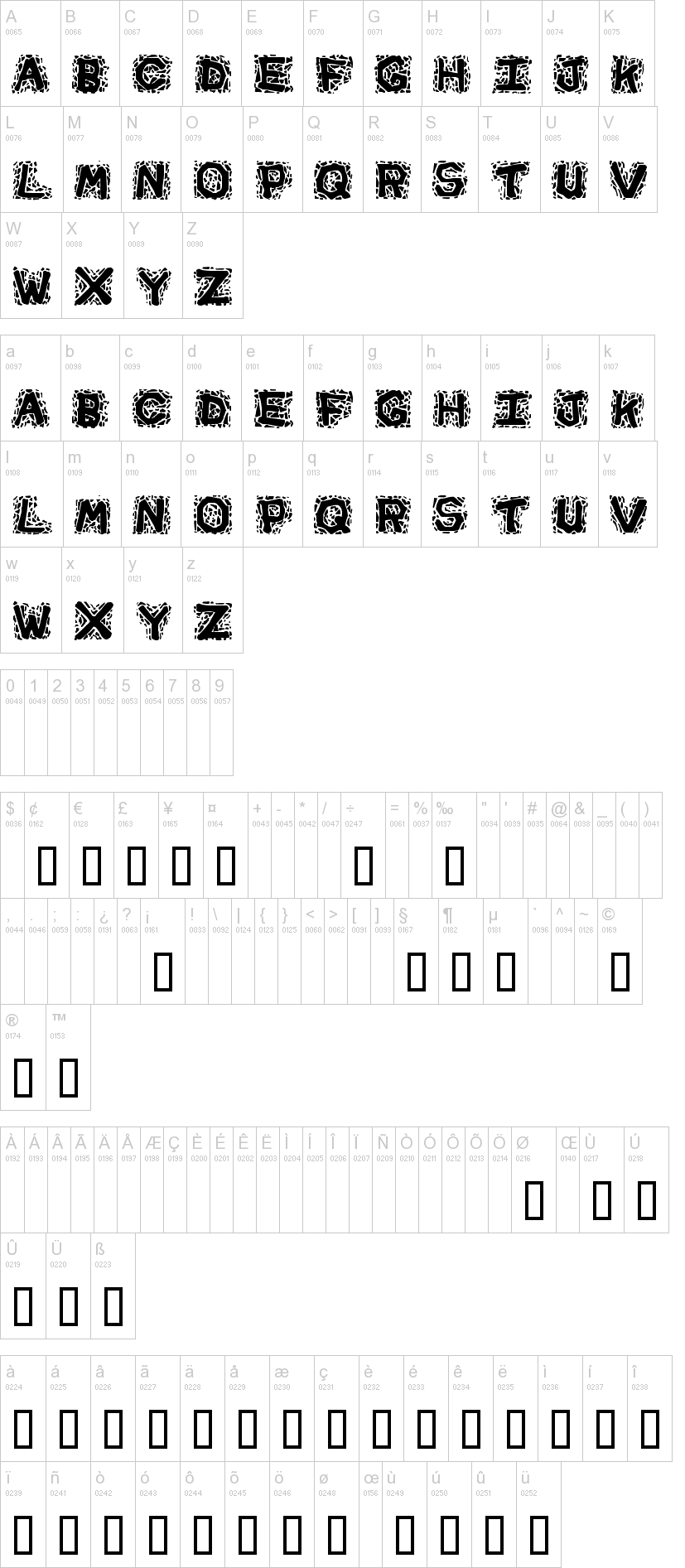
Gravel是一款非常粗野的英文字体,它的特点是比较粗糙的线条,以及粗犷的外观。它的字体设计灵感来自于摩登时期的英式海报,它拥有独特的粗犷外观,在设计中能够起到非常好的突出效果。Gravel字体适合在现代设计中使用,它能够带来摩登时期的复古风格,也能够搭配现代设计风格,使设计更加丰富多彩。内容介绍
Gravel是一款非常不错的手写艺术字体,具有很好的视觉感,适合于文化类的宣传设计、商业类品牌的广告和产品包装设计以及个性化文字排版等较多场景。